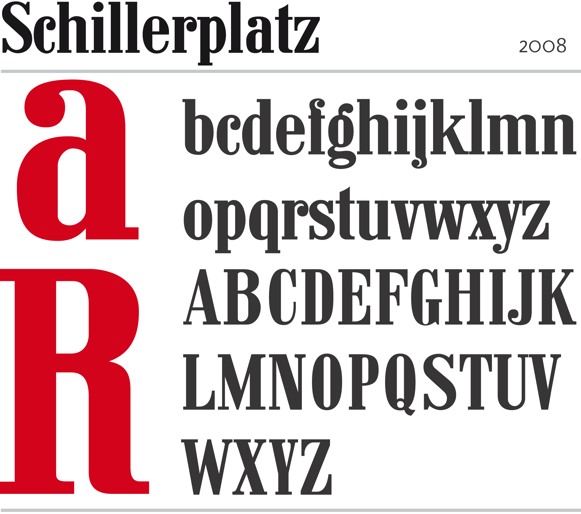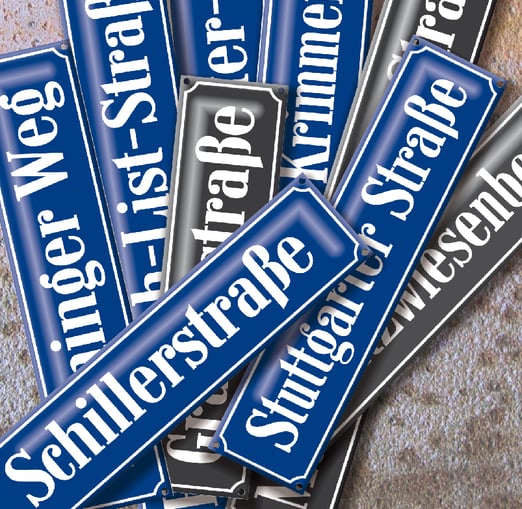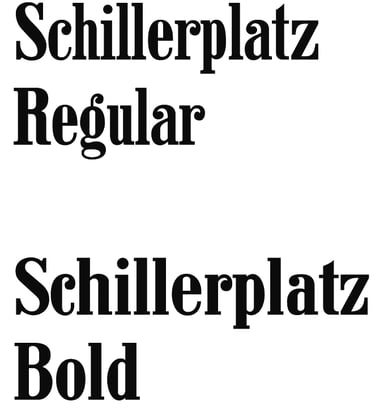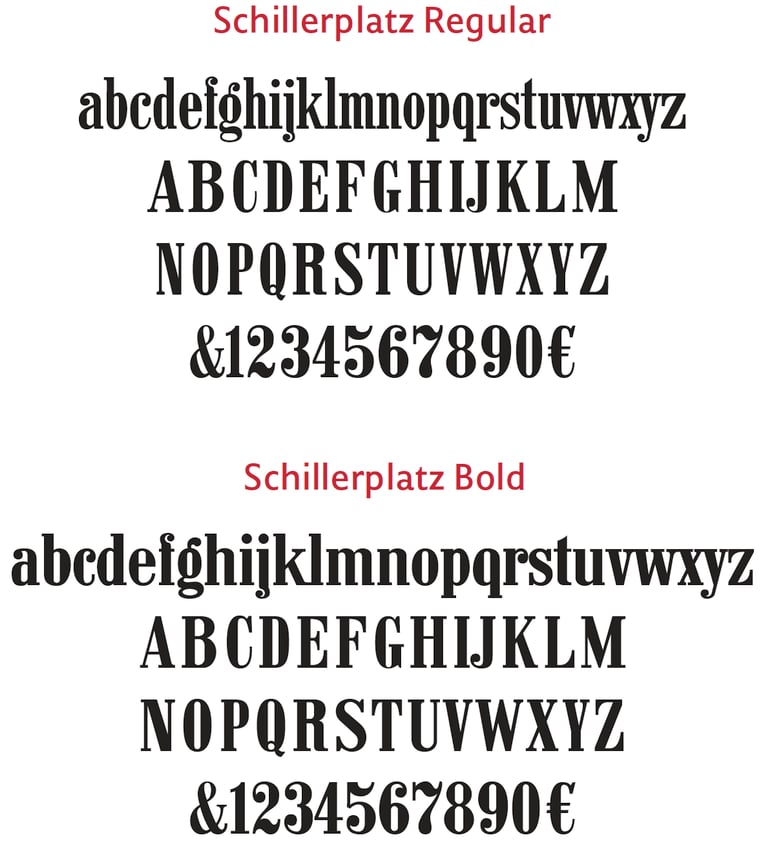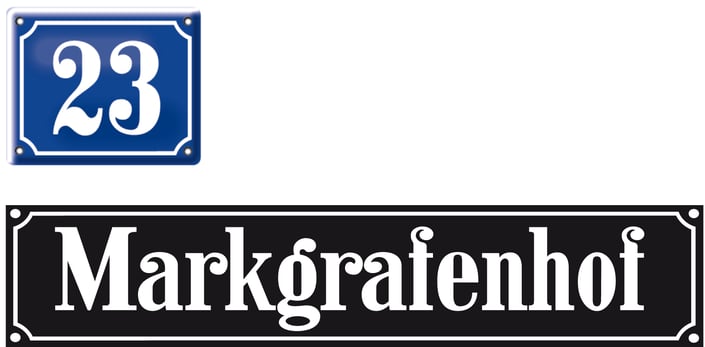
Schillerplatz
Seit längerem sind mir in Backnang die emaillierten Straßenschilder aus der Zeit zwischen den 1930er- und 50er-Jahren aufgefallen, weil häufig die Straßennamen falsch geschrieben sind. 2007 bekam ich den Auftrag, für zwei neue Schilder die Schriftzüge »Stiftshof« und »Markgrafenhof« im Stil der historischen Straßenschilder zu zeichnen. Ich habe also möglichst viele dieser Schilder fotografiert. Es zeigten sich im Wesentlichen zwei Formen, eine schmalere und eine etwas fettere. Der handgemachte, holprige Duktus gibt diesen Schriftzügen den besonderen Charme. Die passenden Ziffern finden sich auf den typischen emaillierten Hausnummern, die vermutlich von der gleichen Firma stammen wie die Straßenschilder.